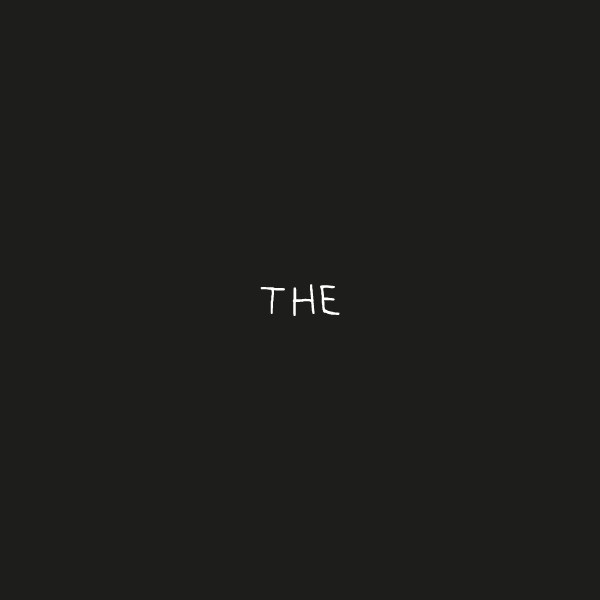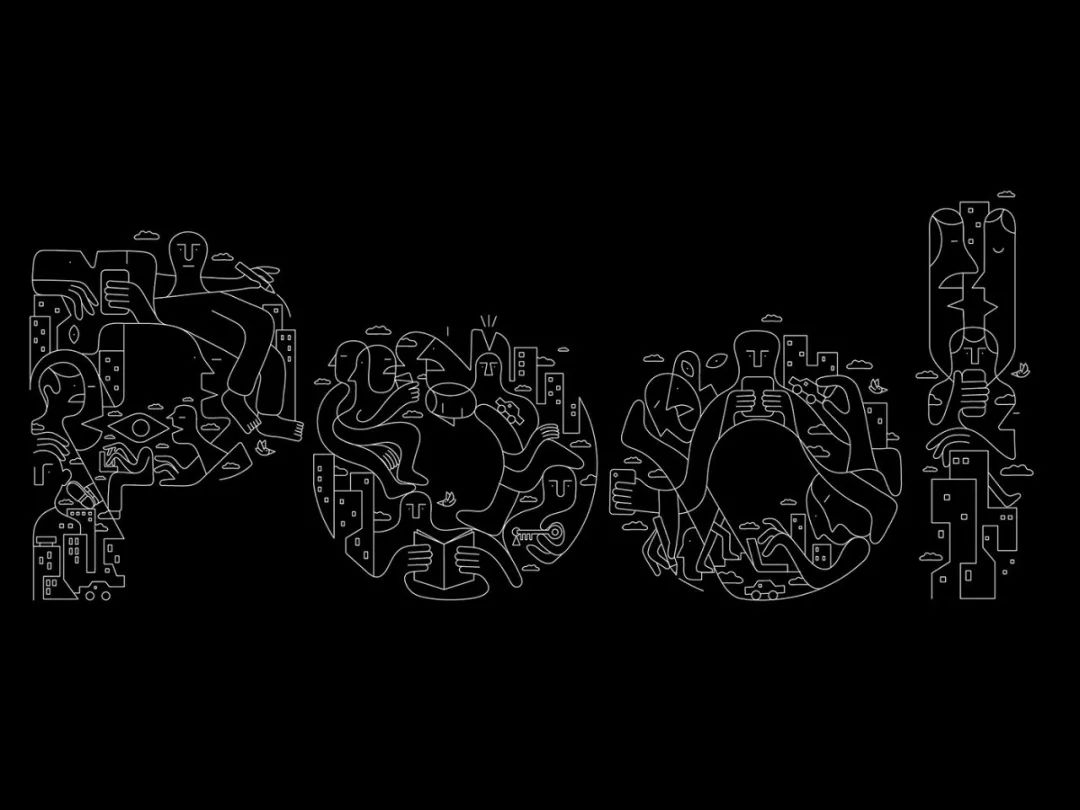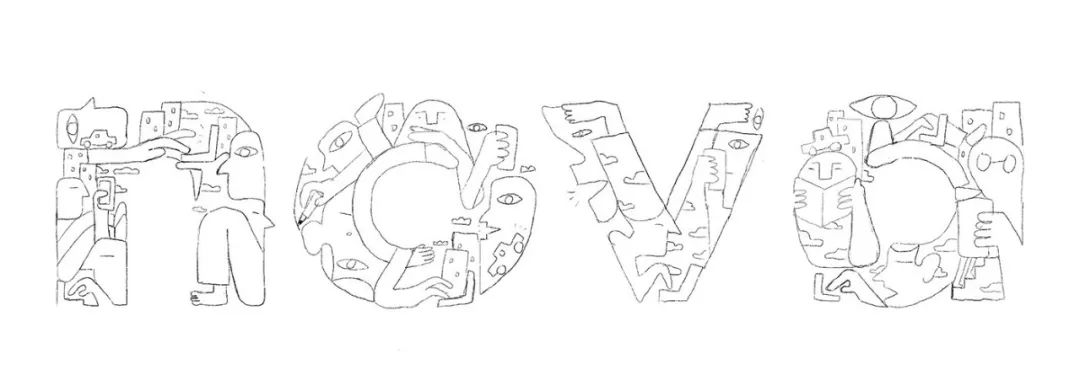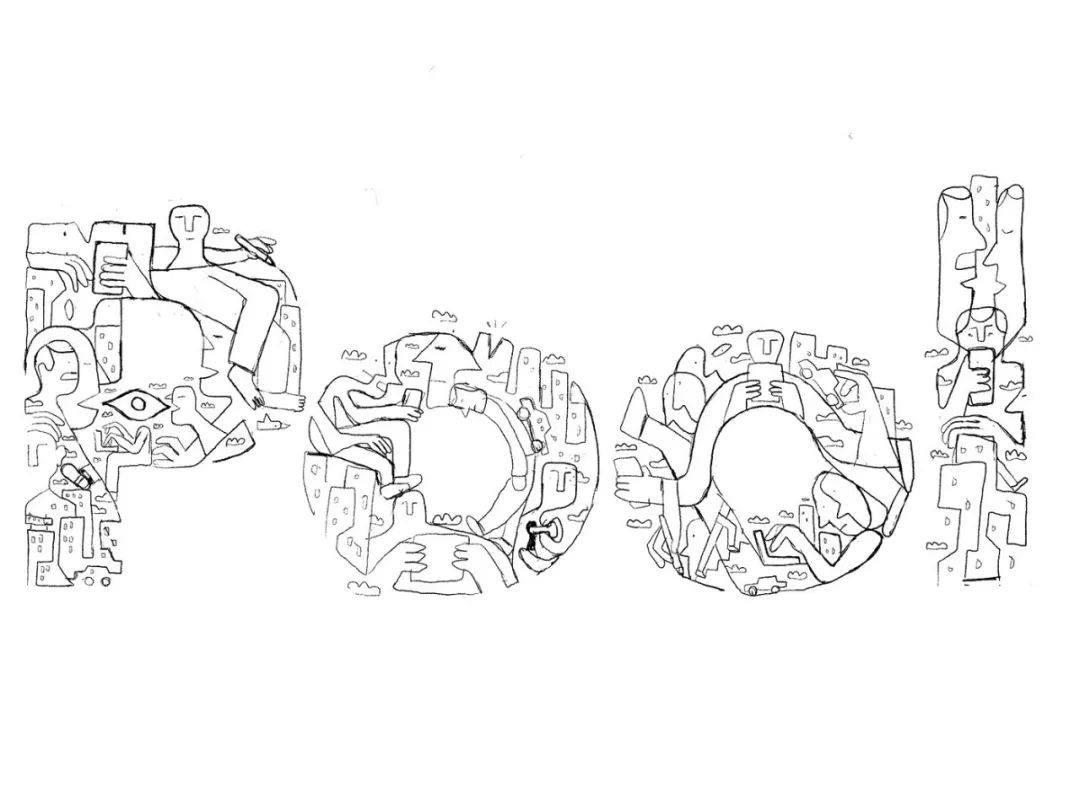
一套音乐专辑的动态字体设计案例分享
设计师Jonathan Calugi为Jazzanova的新专辑“The Pool”设计制作了所有视觉素材。
这套视觉中的惊人的动画部分,由Simone Brillarelli一起完成的。
视觉的设计以“POOL”的字母组合为基础,运用各种系列的小元素组合成字母的外形,通过动态的展现,活泼、自然。
完整专辑设计中使用的系列元素。